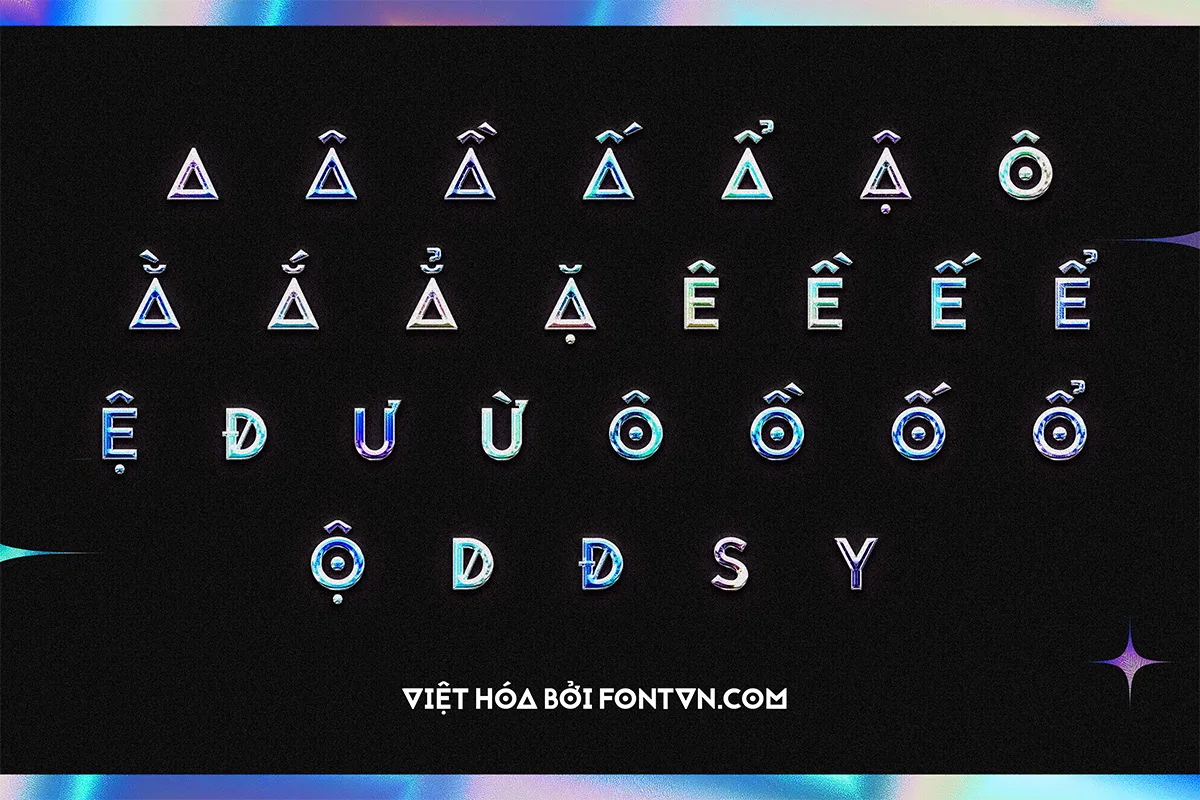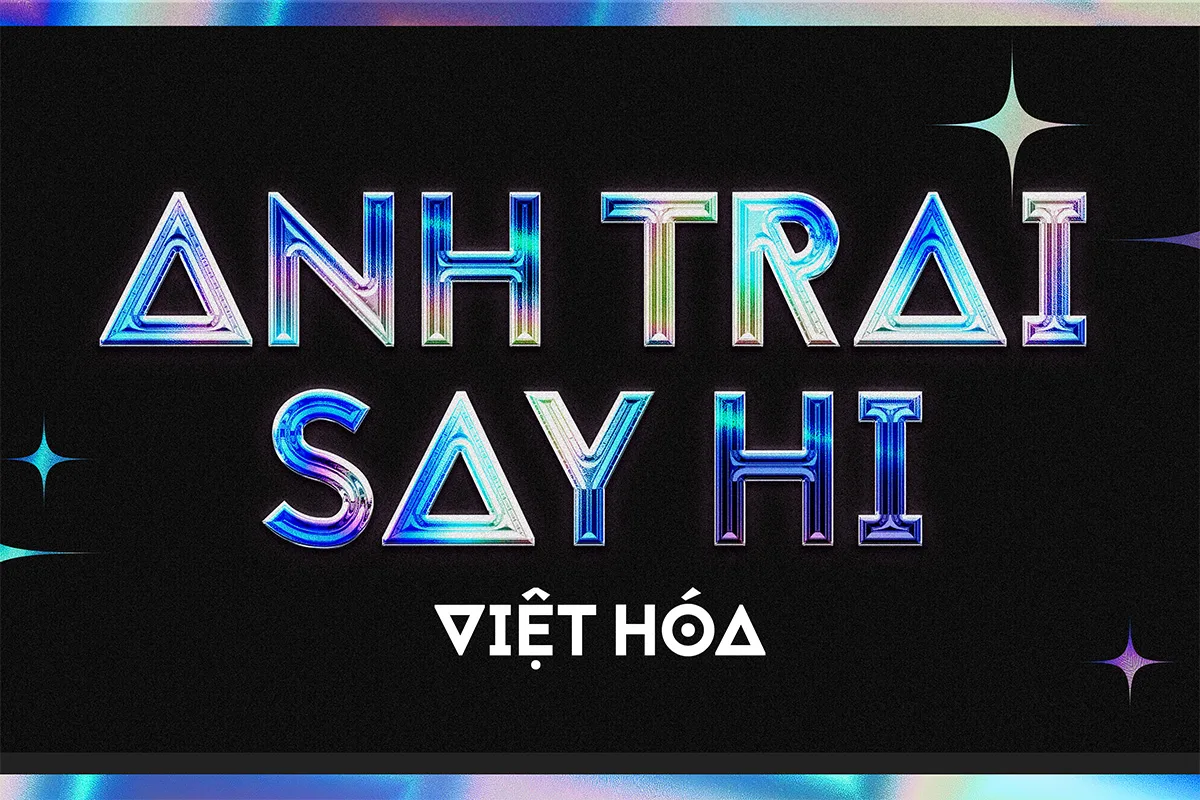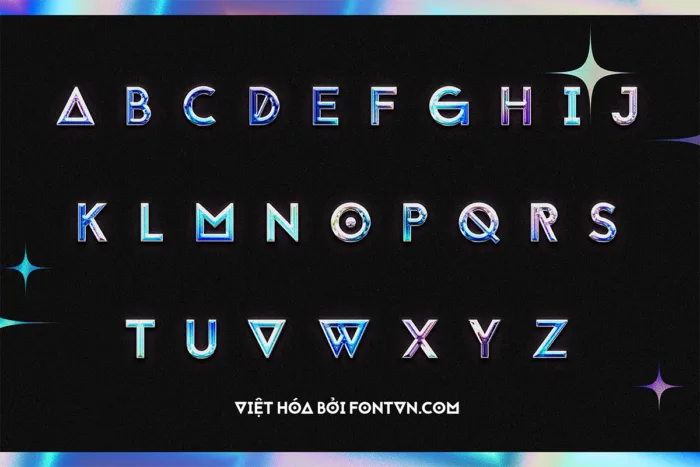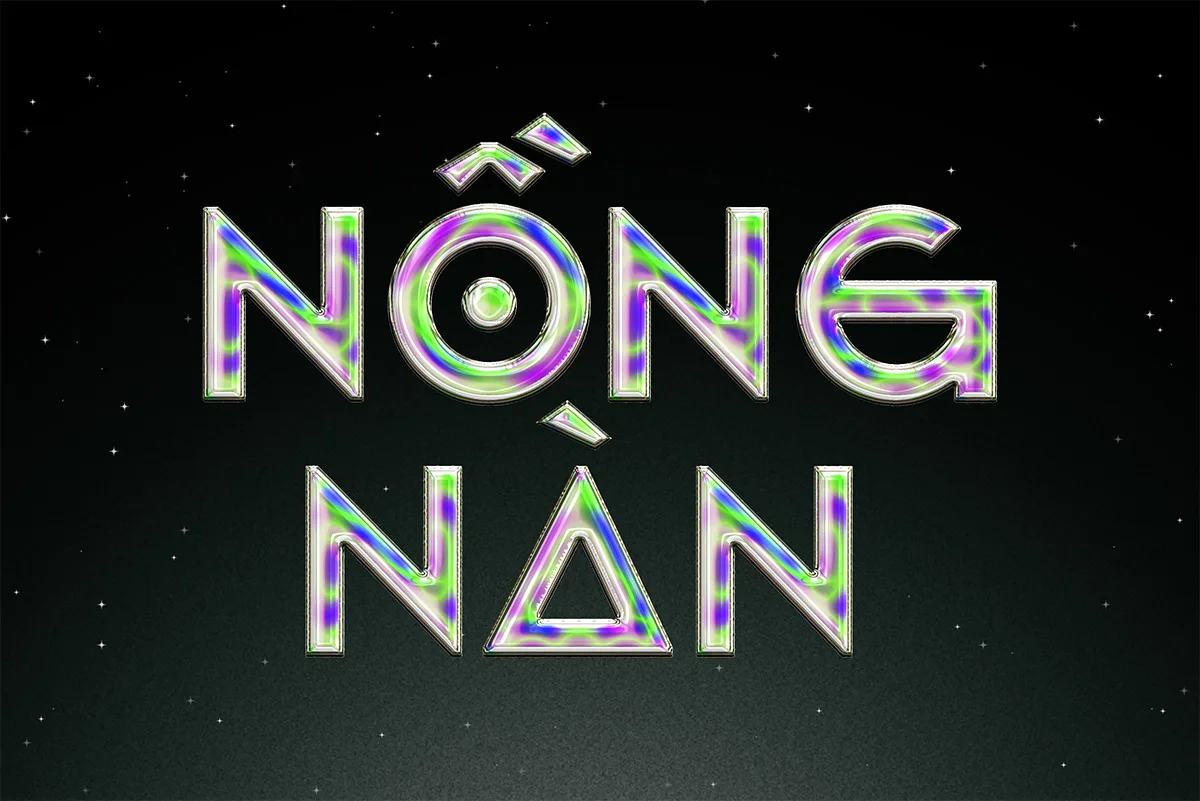
DVN Jaapokki Việt hóa – Font chữ Anh Trai Say Hi
DVN Jaapokki Việt Hóa mang phong cách futuristic kết hợp với hiệu ứng chrome kim loại đa sắc, tạo nên diện mạo lung linh và bắt mắt. Bộ font giữ nguyên tinh thần hình khối của Jaapokki gốc, nhưng được thêm thắt hiệu ứng ánh sáng phản chiếu nhiều màu, khiến từng ký tự trông như được cắt gọt từ kim loại sáng bóng.
Font thích hợp để sử dụng trong:
• Thiết kế poster, bìa album, banner sự kiện âm nhạc
• Typography mang phong cách retro-futurism hoặc cyberpunk
• Tiêu đề, logo, chữ trang trí trong các ấn phẩm nghệ thuật số
Bản Việt hóa đầy đủ dấu tiếng Việt, giúp bạn dễ dàng sử dụng cho thiết kế mang hơi hướng điện tử, mộng mị và hiện đại. Font này được dùng cho chương trình Anh trai say hi và đang được nhiều bạn trẻ ưa chuộng.
Font có 2 phiên bản dấu cho bạn lựa chọn.